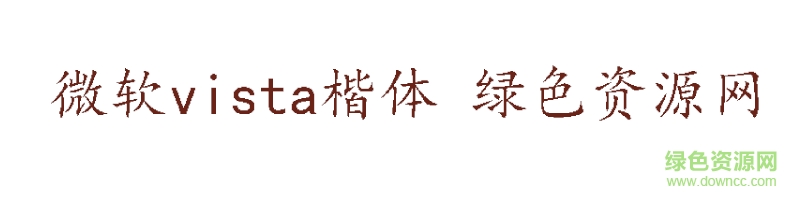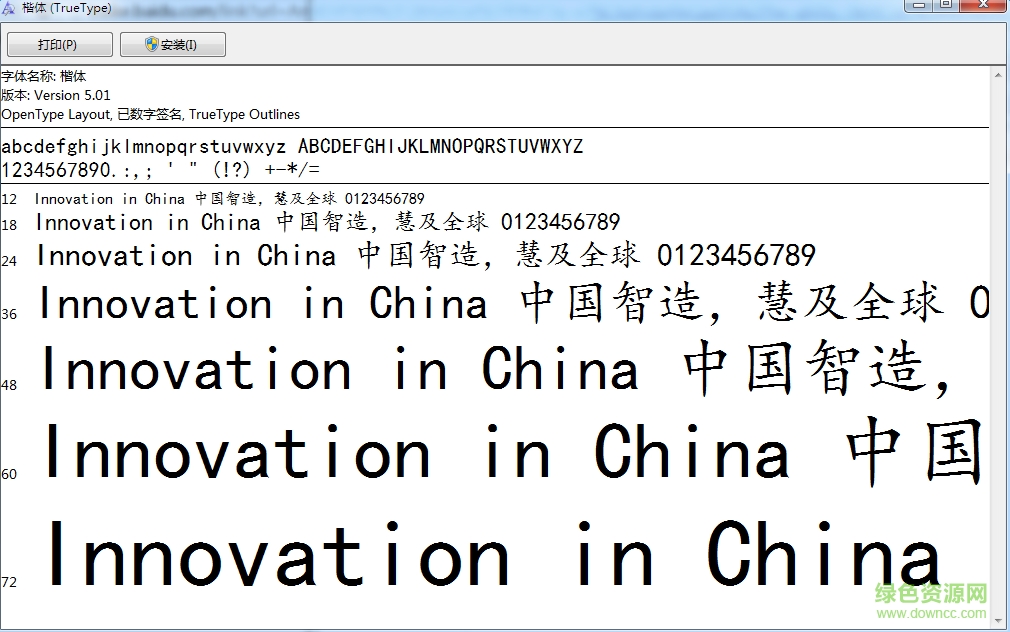
微軟vista楷體是一款字形非常優(yōu)美的楷體字體,完全具備楷體形體方正,筆畫平直的特點(diǎn),有喜歡這款字體的朋友可以來(lái)綠色資源網(wǎng)下載安裝!
微軟vista楷體是應(yīng)用于設(shè)計(jì)方面的中文簡(jiǎn)體漢字,字形端正大方,可用于平面設(shè)計(jì)、名片設(shè)計(jì)、廣告創(chuàng)意、印刷包裝等領(lǐng)域!